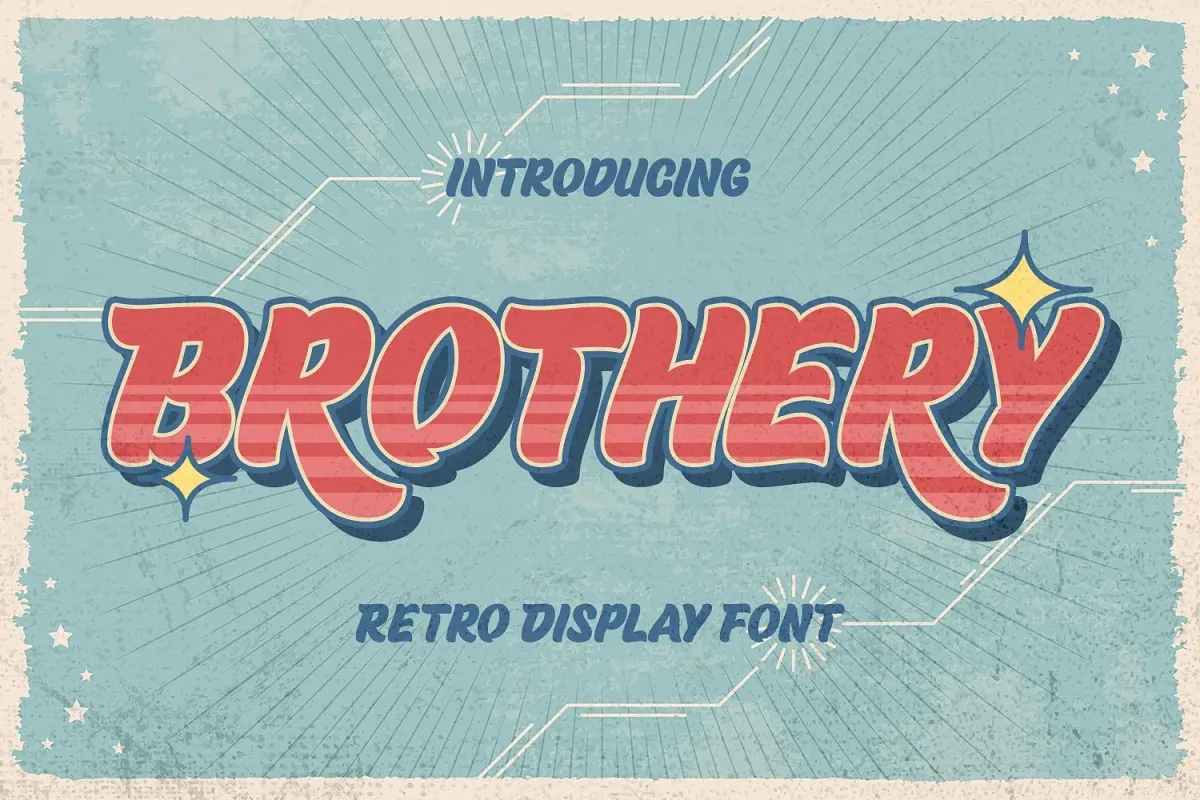
A Brothery Font é uma elegante tipografia para destaque desenvolvida de forma artesanal com fins únicos. Este tipo de letra vem equipado com múltiplas ligaturas e alternativas que lhe proporcionam um estilo único e extra criativo. Ideal para qualquer projeto de design, seja para convites, logomarca, capa de livro, artefato ou qualquer outra finalidade visual. Uma fonte de destaque ideal para tornar seus projetos singulares e impecáveis, se você está procurando por uma maneira de dar um toque a mais em suas criações.